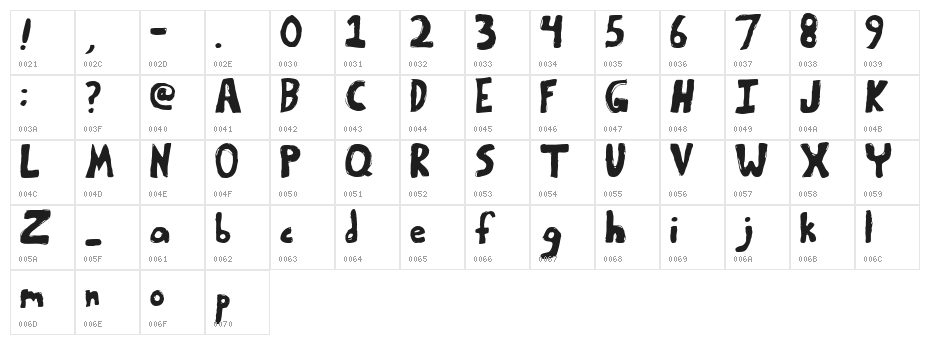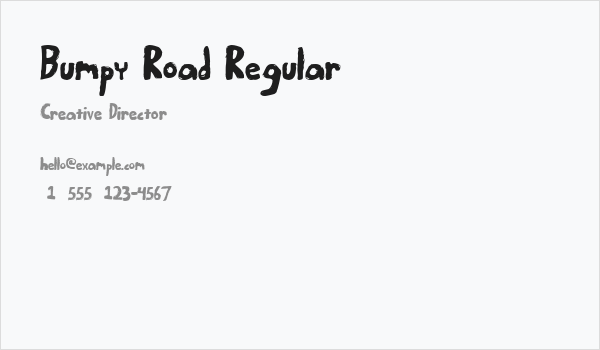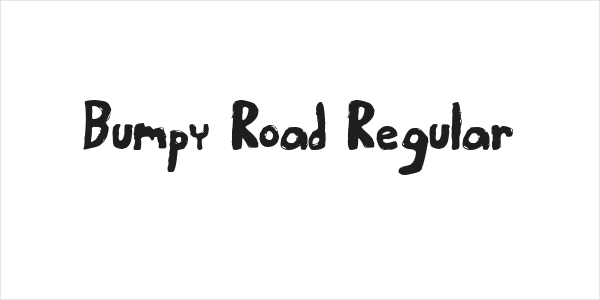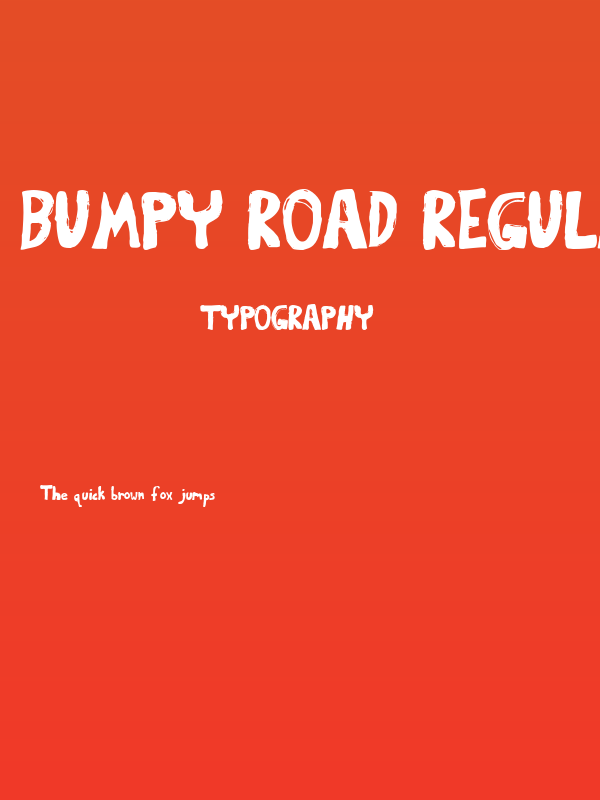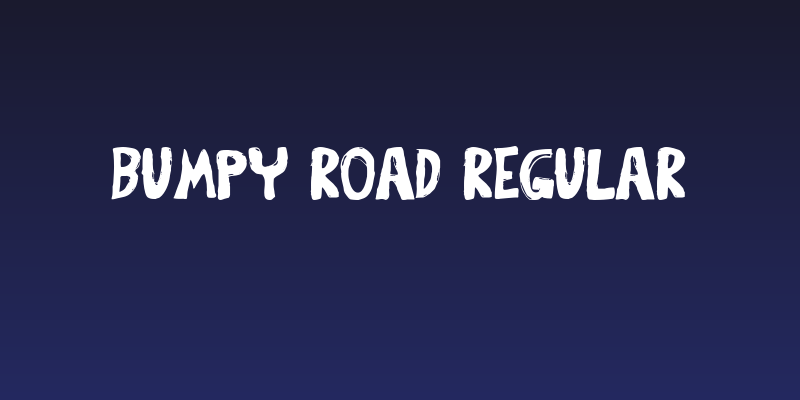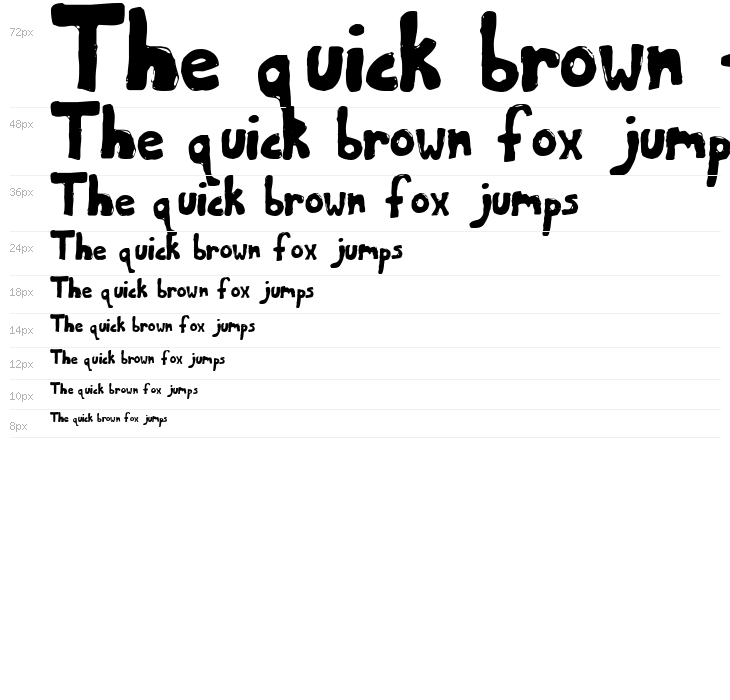
Bumpy Road Regular Font
| الاسم | Bumpy Road Regular |
| مشاريع مقترحة | Ideal for children's books, playful branding, artistic posters, and creative invitations. |